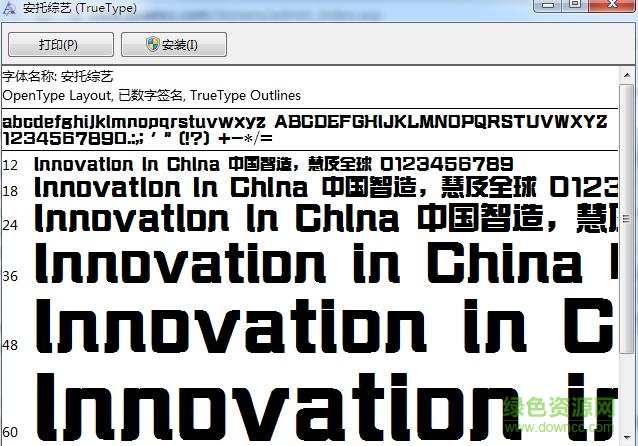
安托綜藝字體是一款看上去非常醒目的中文字體,具有整齊、雄壯、厚重的特色,整體看上去非常的美觀,有需要的朋友歡迎下載使用!
安托綜藝字體是一款字形非常有特色的綜藝字體,以黑體為基本出發(fā)點(diǎn),外觀更趨方正,外張,結(jié)構(gòu)與筆劃更善于平均分布,擺脫了傳統(tǒng)黑體之規(guī)范,更具自由,適用于一般海報(bào),報(bào)紙,雜志標(biāo)題!